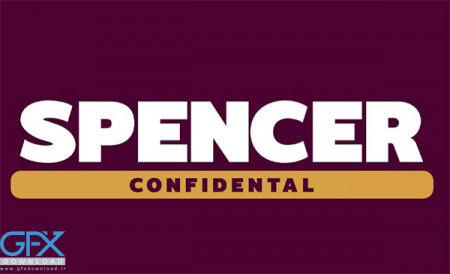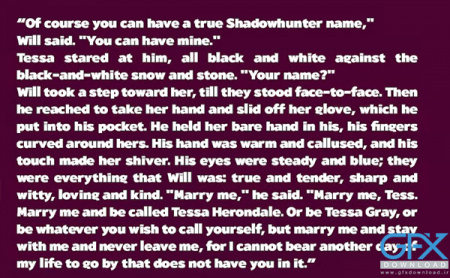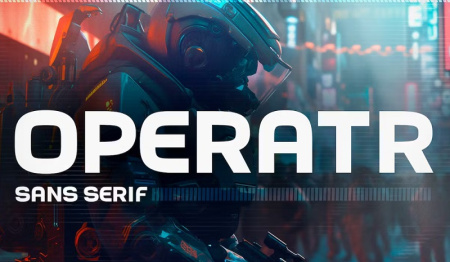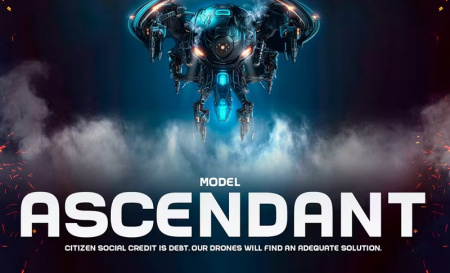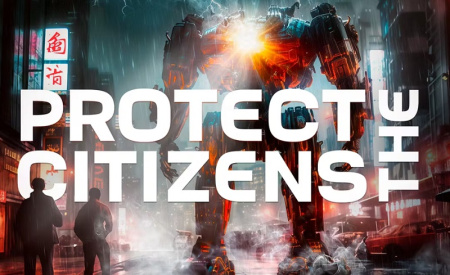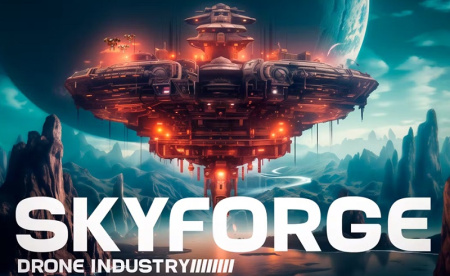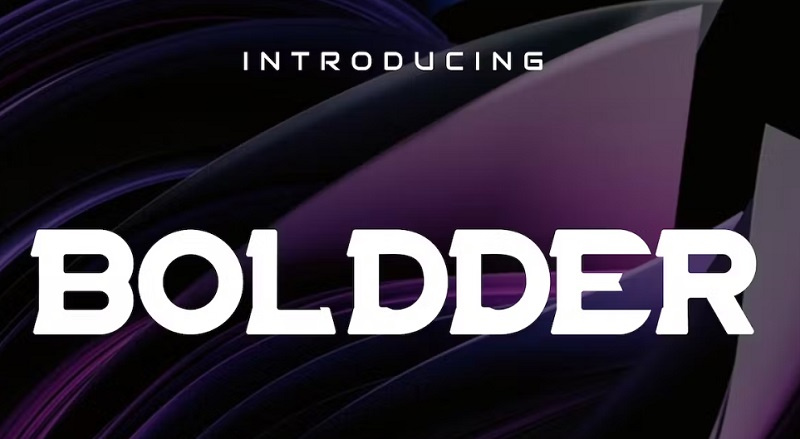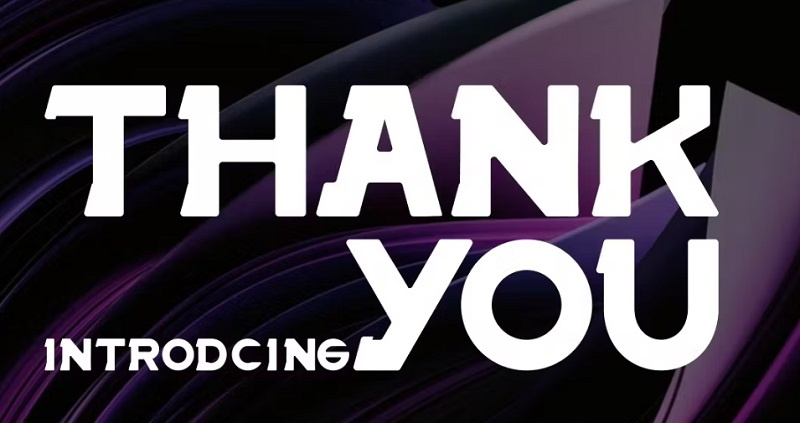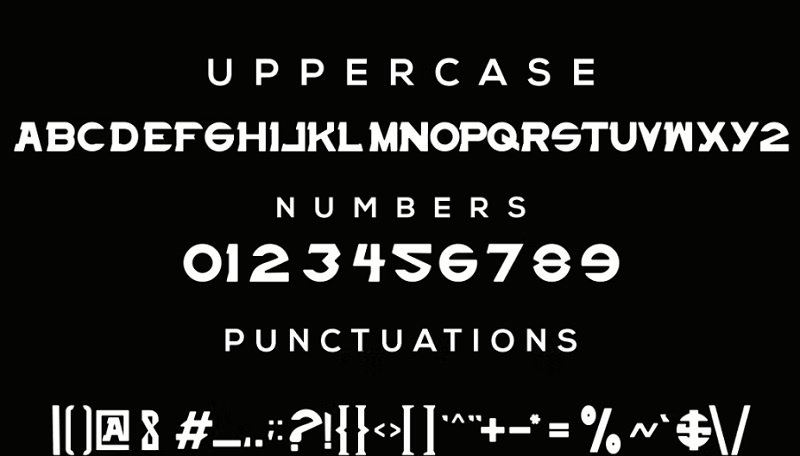
دانلود فونت انگلیسی پررنگ Hugein. این مجموعه شامل 2 فونت انگلیسی پررنگ و بولد با طراحی مدرن sans serif است. این فونت ها با طراحی برجسته، کاراکتر های سرگرم کننده یک کار خلاقانه به شما می دهد. بیش از 100 زبان چند زبانه پشتیبانی می کند. فونت پررنگ انگلیسی برای طراحی لوگو، رسانه های اجتماعی، عنوان فیلم، عنوان کتاب، یک متن کوتاه مناسب است. برای مشاهده پیش نمایش این فونت ها از جی اف ایکس دانلود در اداهه مطلب با ما همراه باشید.
1- دانلود فونت انگلیسی پررنگ Hugein
2- فونت انگلیسی پر رنگ و بولد Operatr
فونت انگلیسی پر رنگ و بولد Operatr به طور خاص برای بازی ها، عناوین و سرفصل ها طراحی شده است. عالی برای ترکیب با تصاویر پس زمینه، و آن را به گزینه ای عالی برای پروژه های بصری خیره کننده تبدیل می کند. با Operatr، طرح های شما ظاهری قوی و محکم خواهند داشت. جسارت آن حس هیجان و انرژی را به طراحی هاش شما القا می کند.
3- فونت پررنگ انگلیسی Boldder
Boldder یک فونت زیبای انگلیسی و پر رنگ است که به سبک دست خط زیبا طراحی شده است. این فونت برای نقل قول، دعوت نامه عروسی، طرح های لوگو، عنوان، مجله و موارد دیگر کاملا مناسب است
ویژگی های فونت های پررنگ انگلیسی از جی اف ایکس دانلود